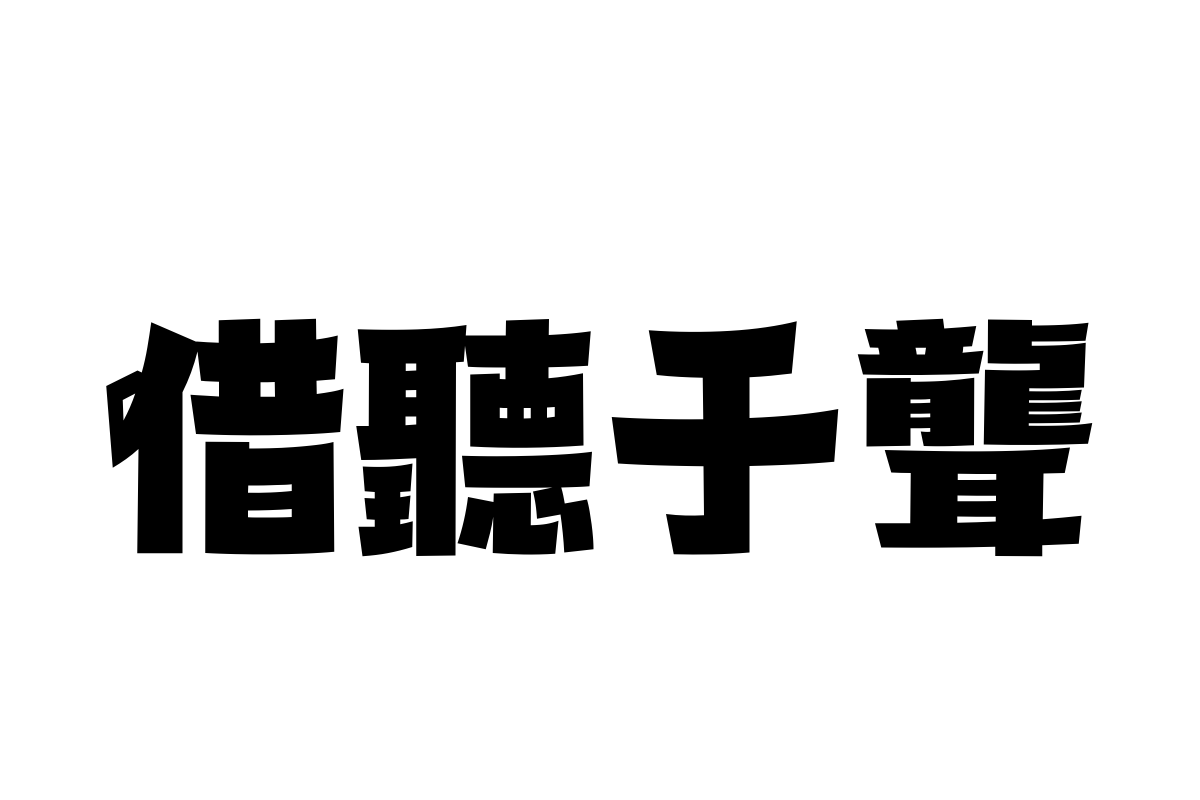
汉仪铸字牛仔繁体是一款具有现代感的字体,它采用了独特的设计风格和排版方式,给人一种时尚、动感的感觉。这款字体的特点是字形简洁明了,线条流畅自然,具有很强的视觉冲击力和辨识度。
在设计上,汉仪铸字牛仔繁体采用了简洁的线条和几何形状,使得整个字体看起来更加干净利落。同时,它还巧妙地融入了一些英文字母的元素,增加了一些国际化的感觉。这种设计使得这款字体不仅适合用于印刷品,也适合用于网络、广告等领域的宣传材料。